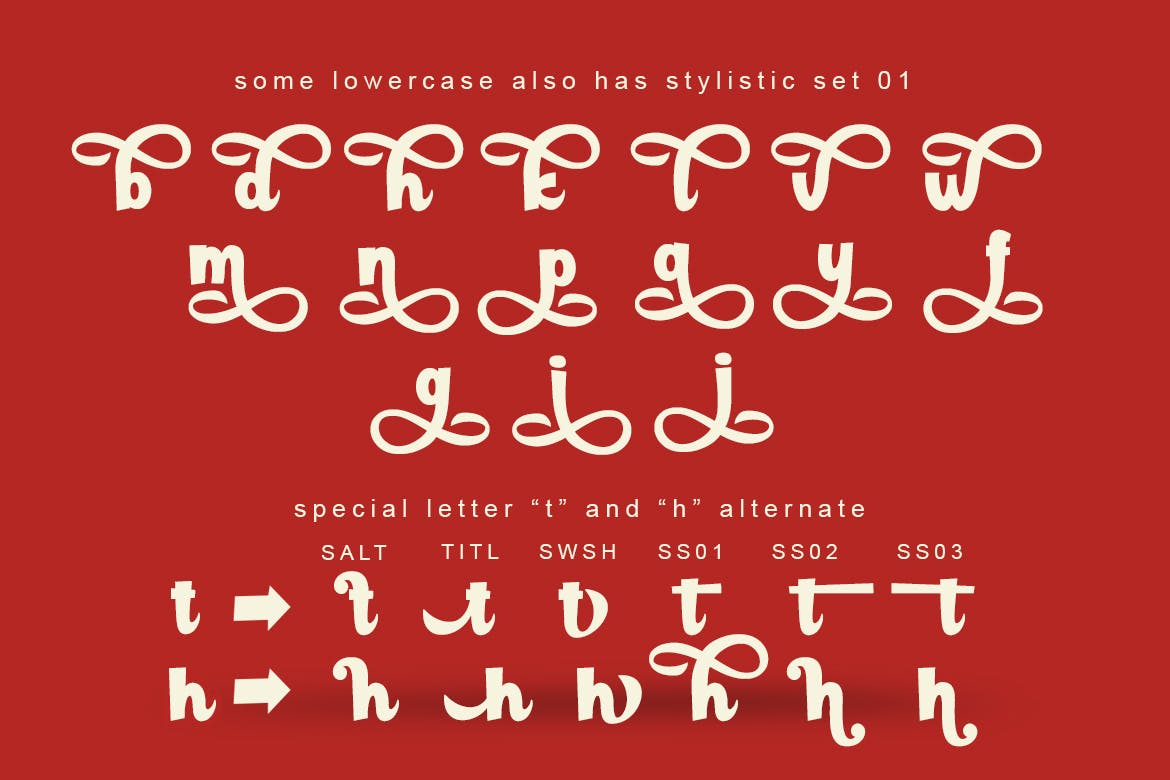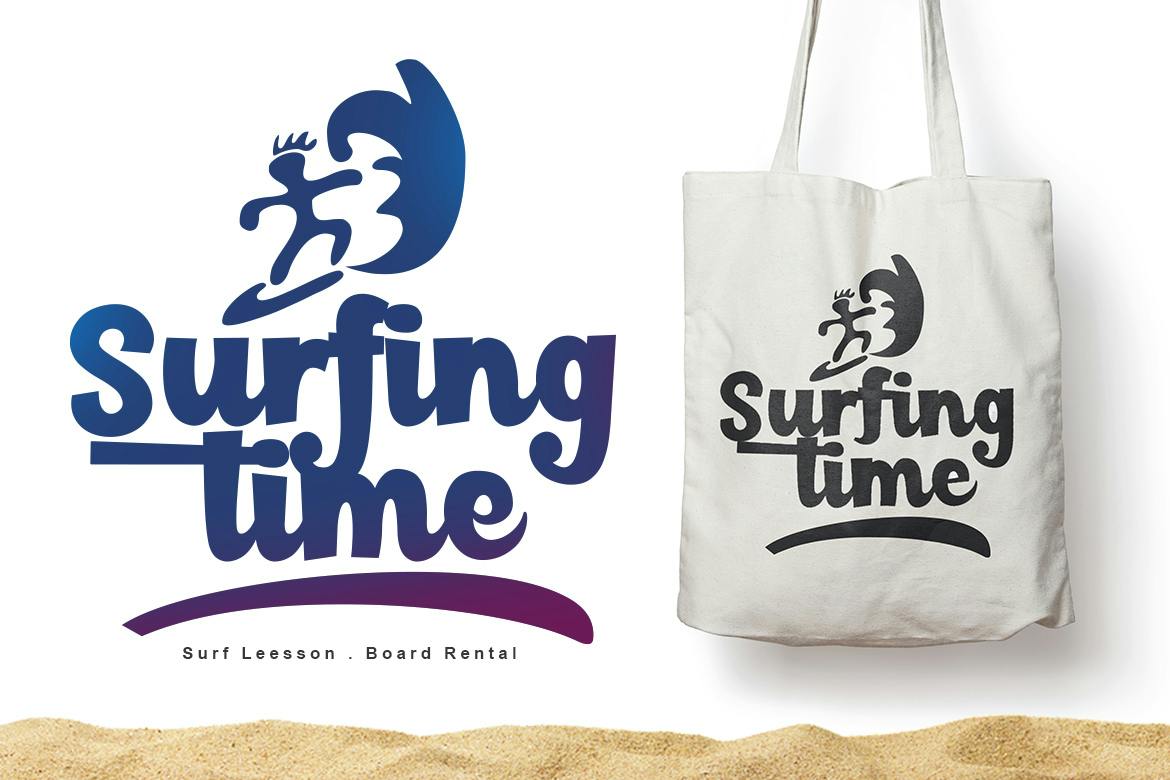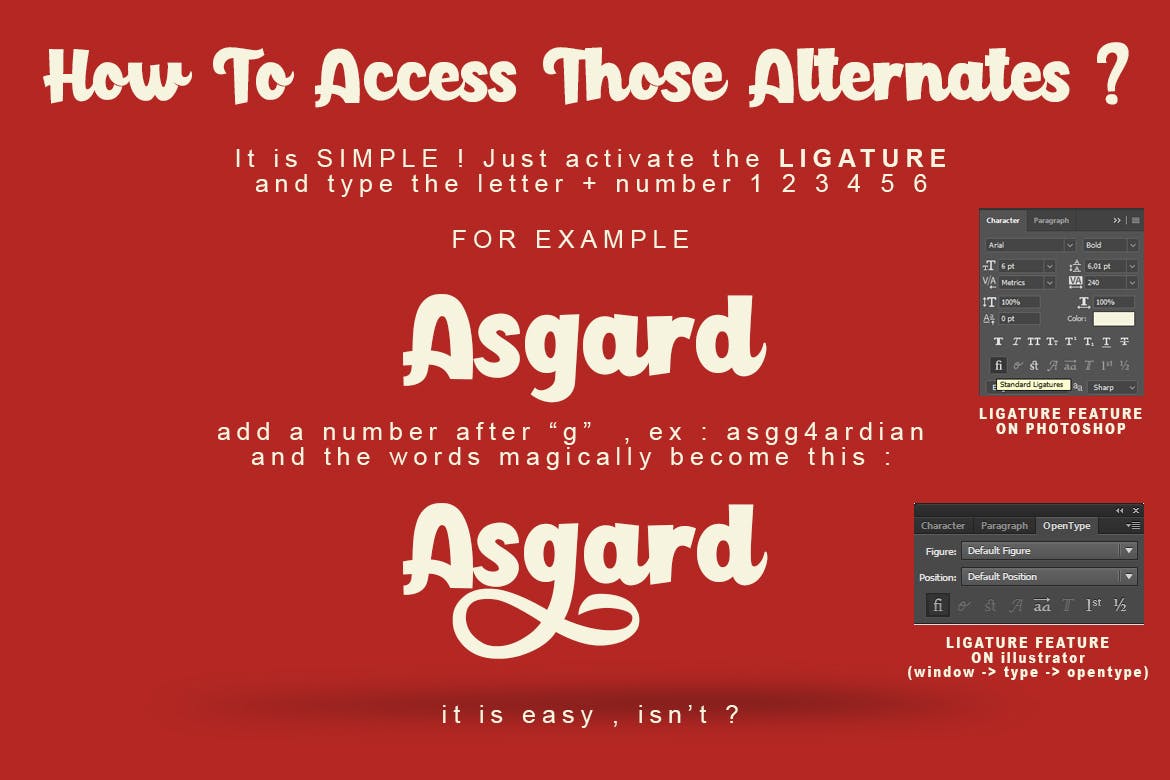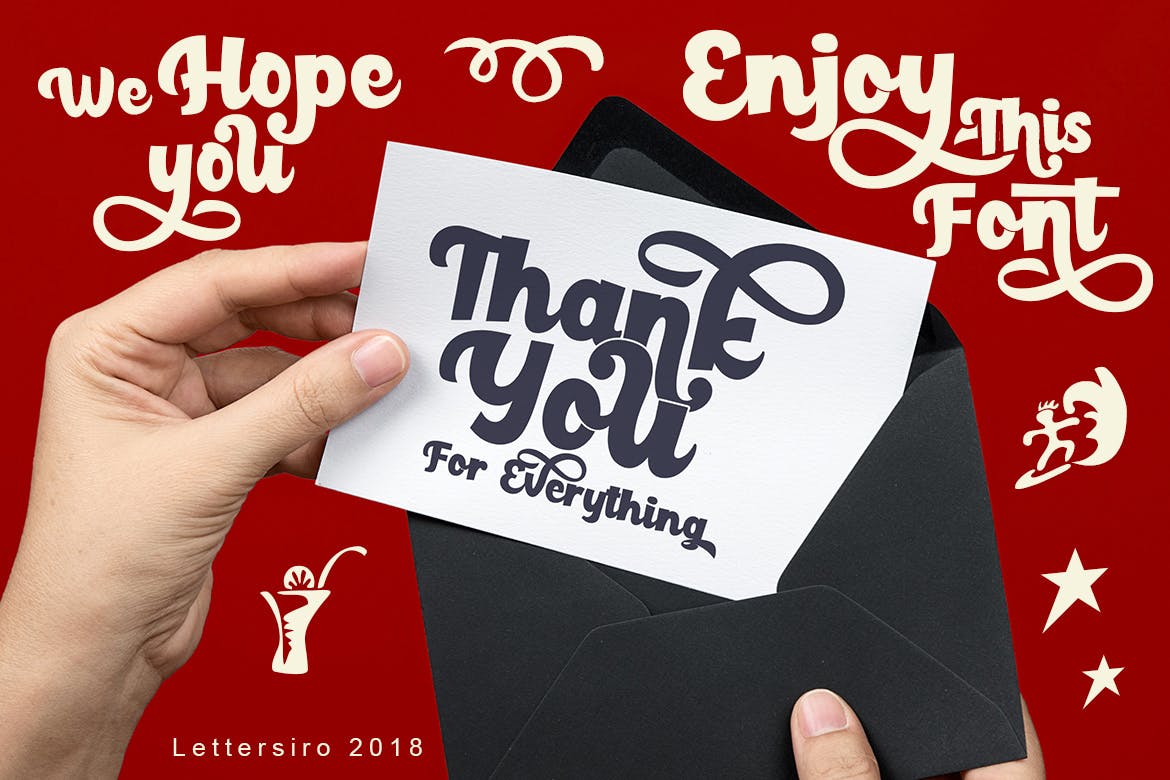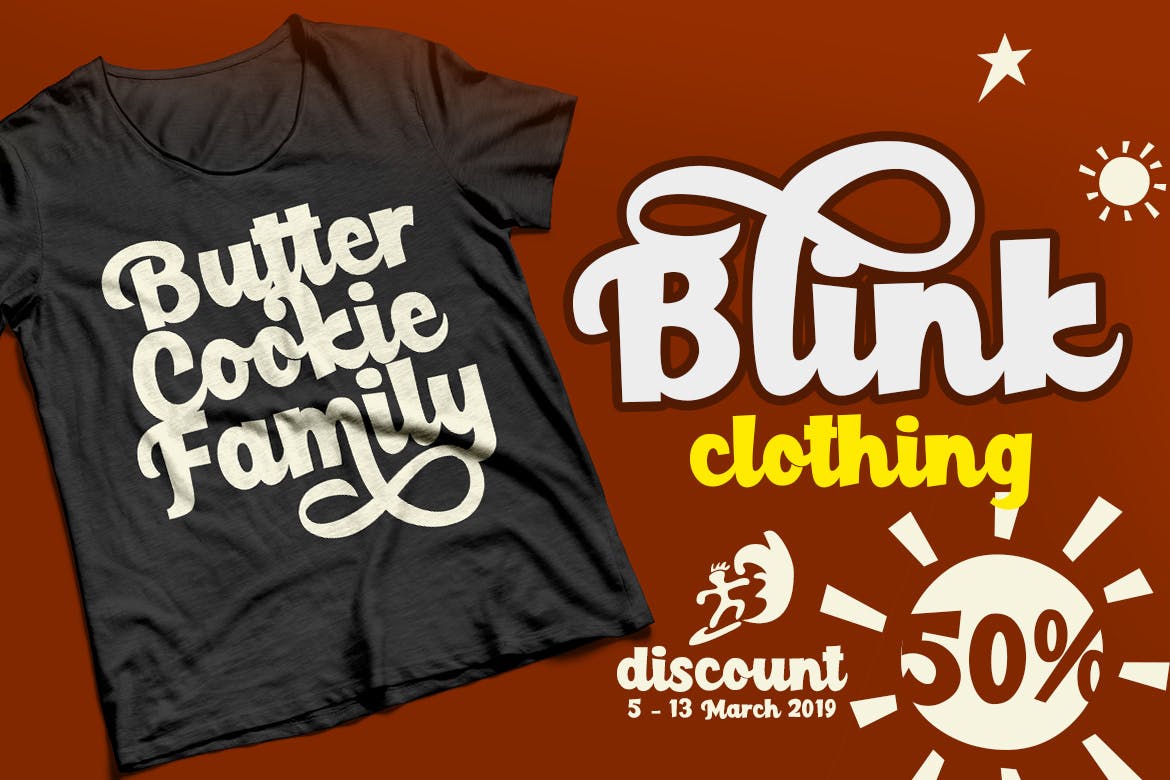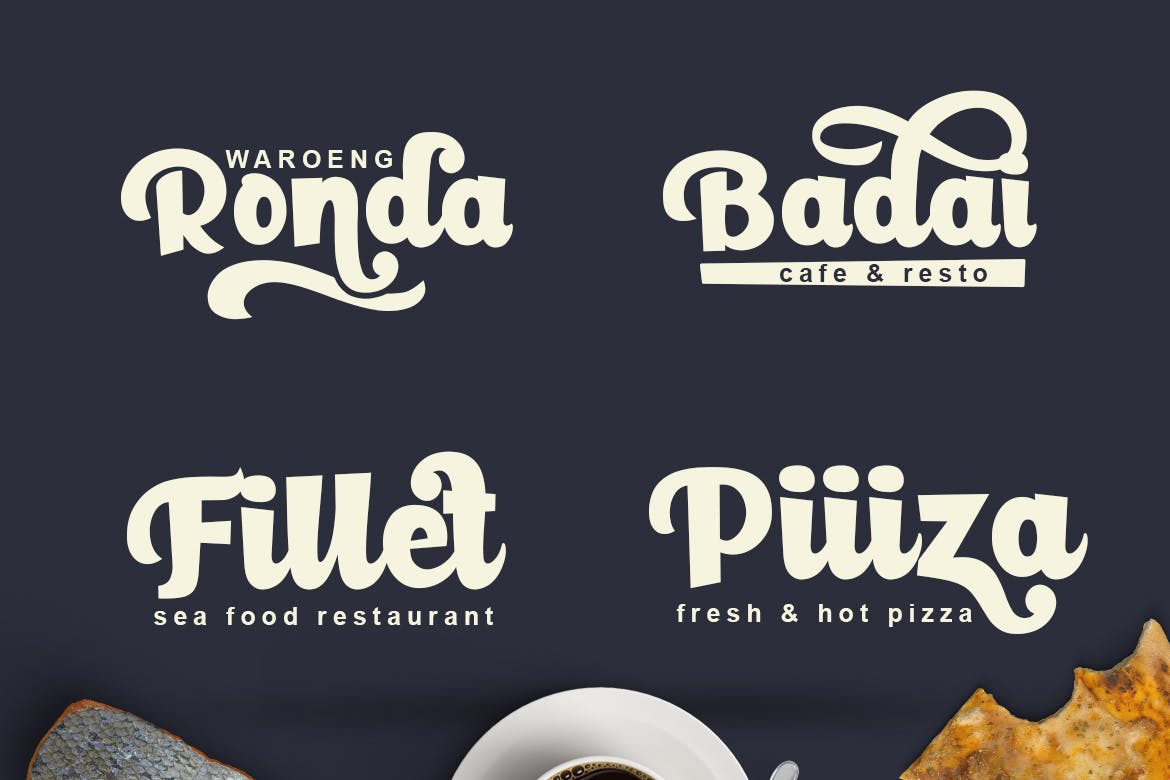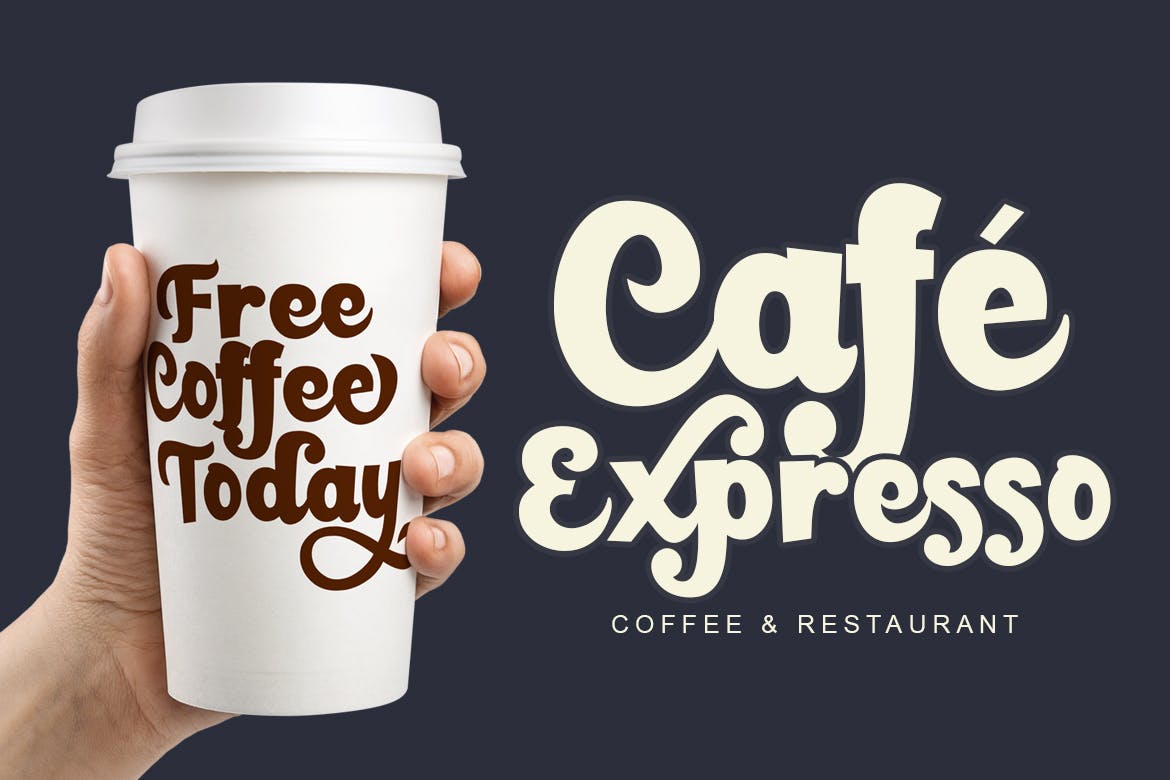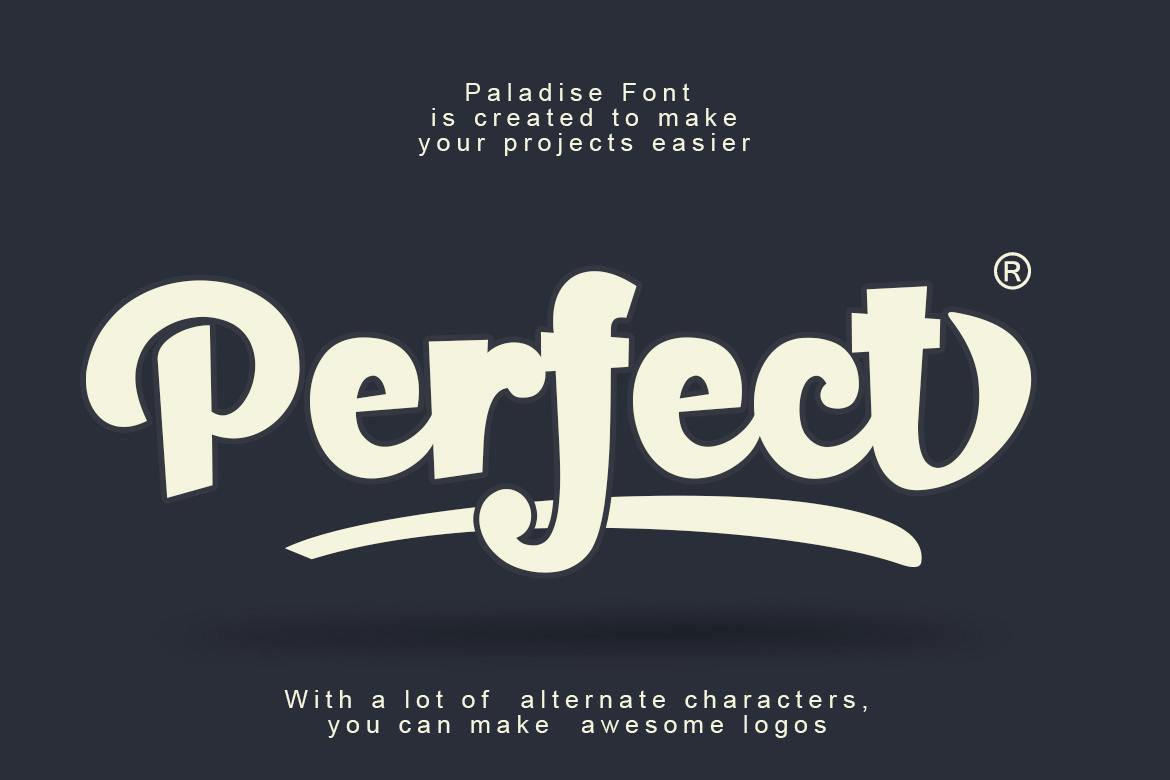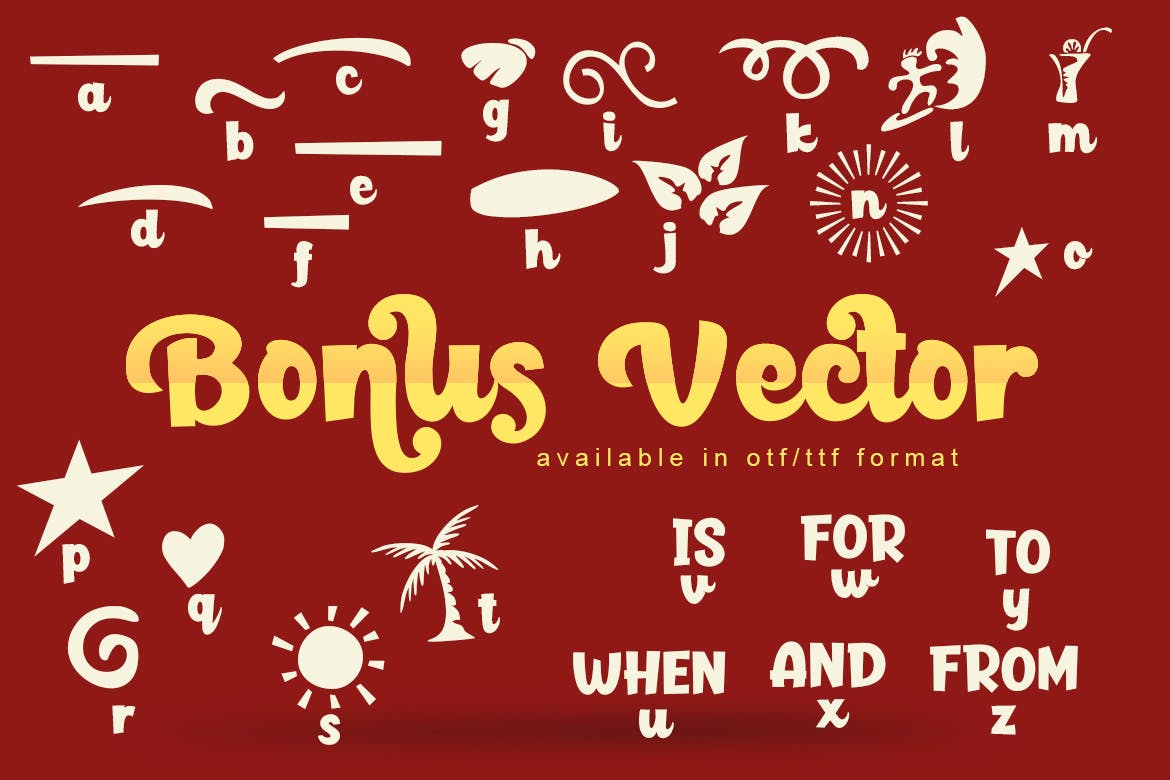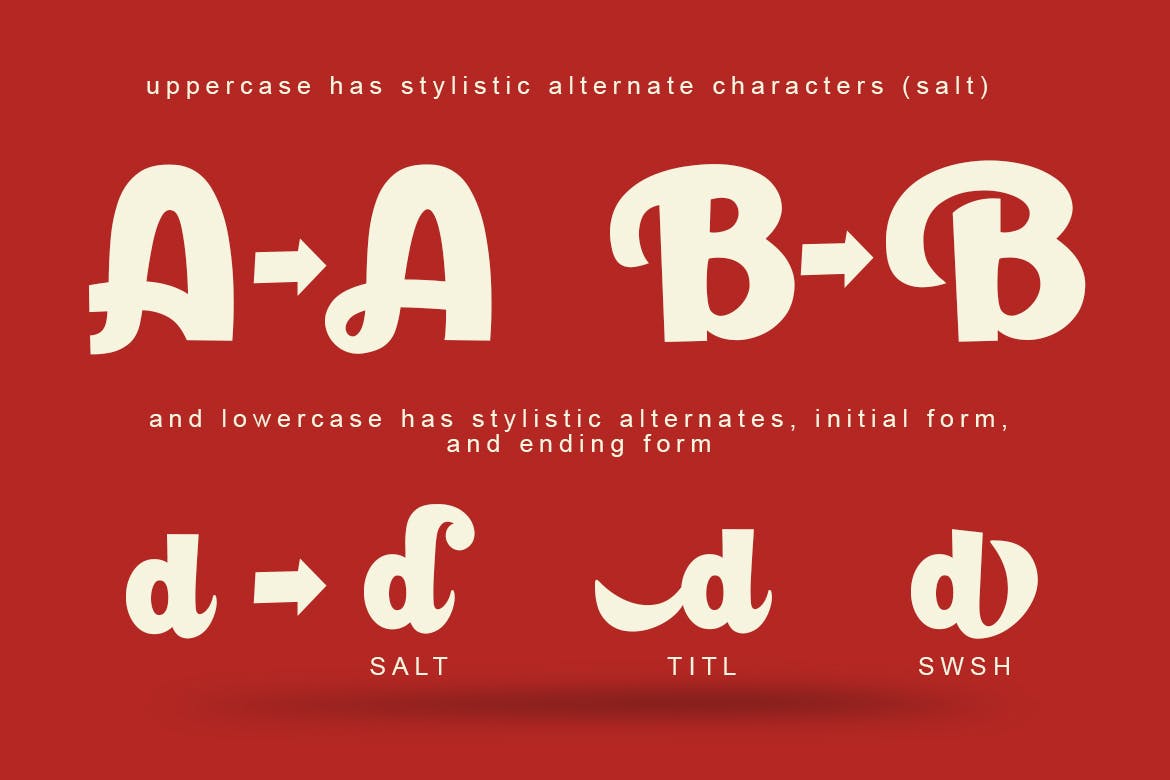
ما یک فونت سرگرمکننده و زیبا به نام پلادیس (Paladise Font) طراحی کردهایم. این فونت برای لوگو، پوستر، لباس، برندینگ، دعوتنامههای مهمانی و بسیاری از پروژههای طراحی دیگر بسیار مناسب است. پلادیس با تعداد زیادی کاراکتر جایگزین و همچنین ۲۶ وکتور اضافی همراه است.
- افزودن سبکهای بیشتر به هر فونت با ویژگیهای OpenType - جایگزینهای سبک، فرم ابتدایی و نهایی حروف کوچک، لیگاتورها و مجموعههای سبک.
- پشتیبانی چندزبانه - پیام خود را به طور جهانی گسترش دهید.